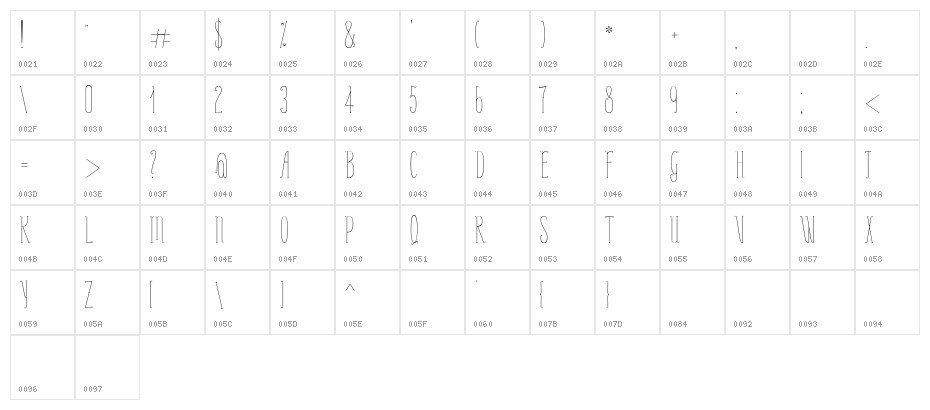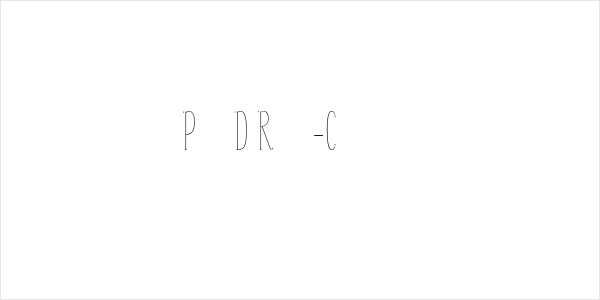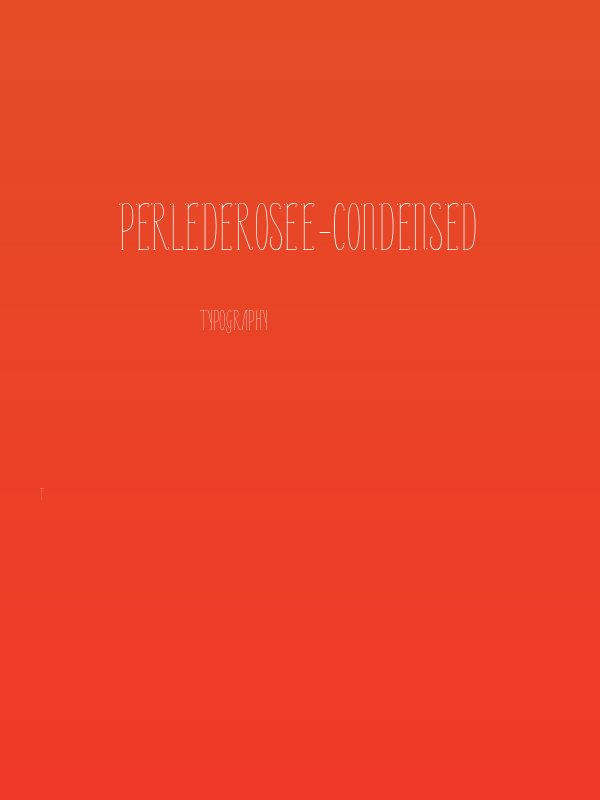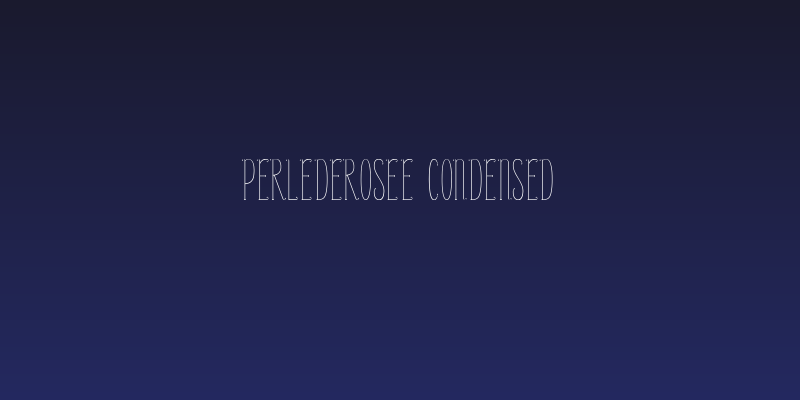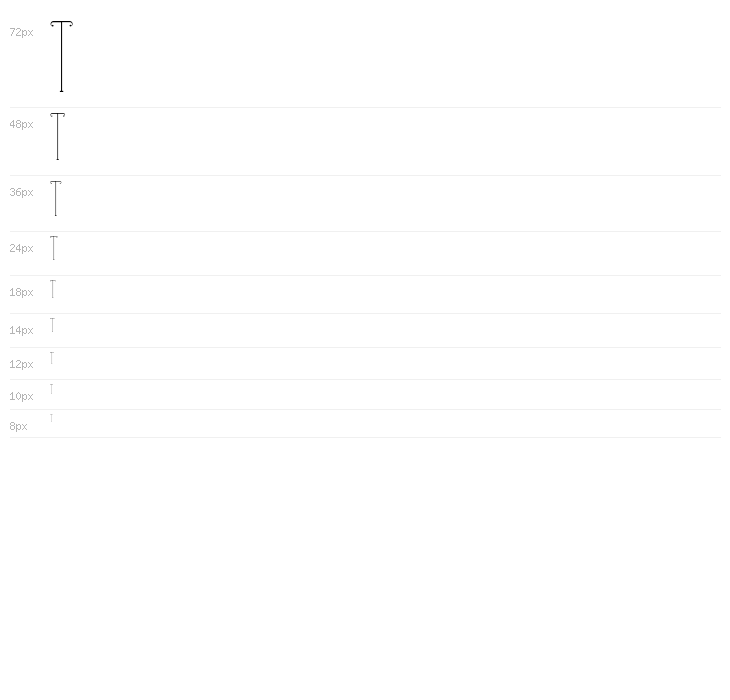
PerleDeRosee-Condensed Font
| Stile generale | Elegant, Sophisticated |
| Caso d'uso | Headlines, Invitations, Branding |
| Progetti proposti | Ideal for wedding invitations, luxury branding, high-end product packaging, and editorial design. |